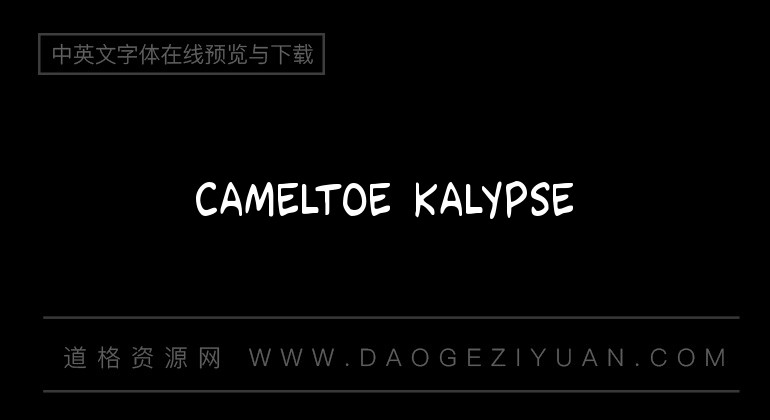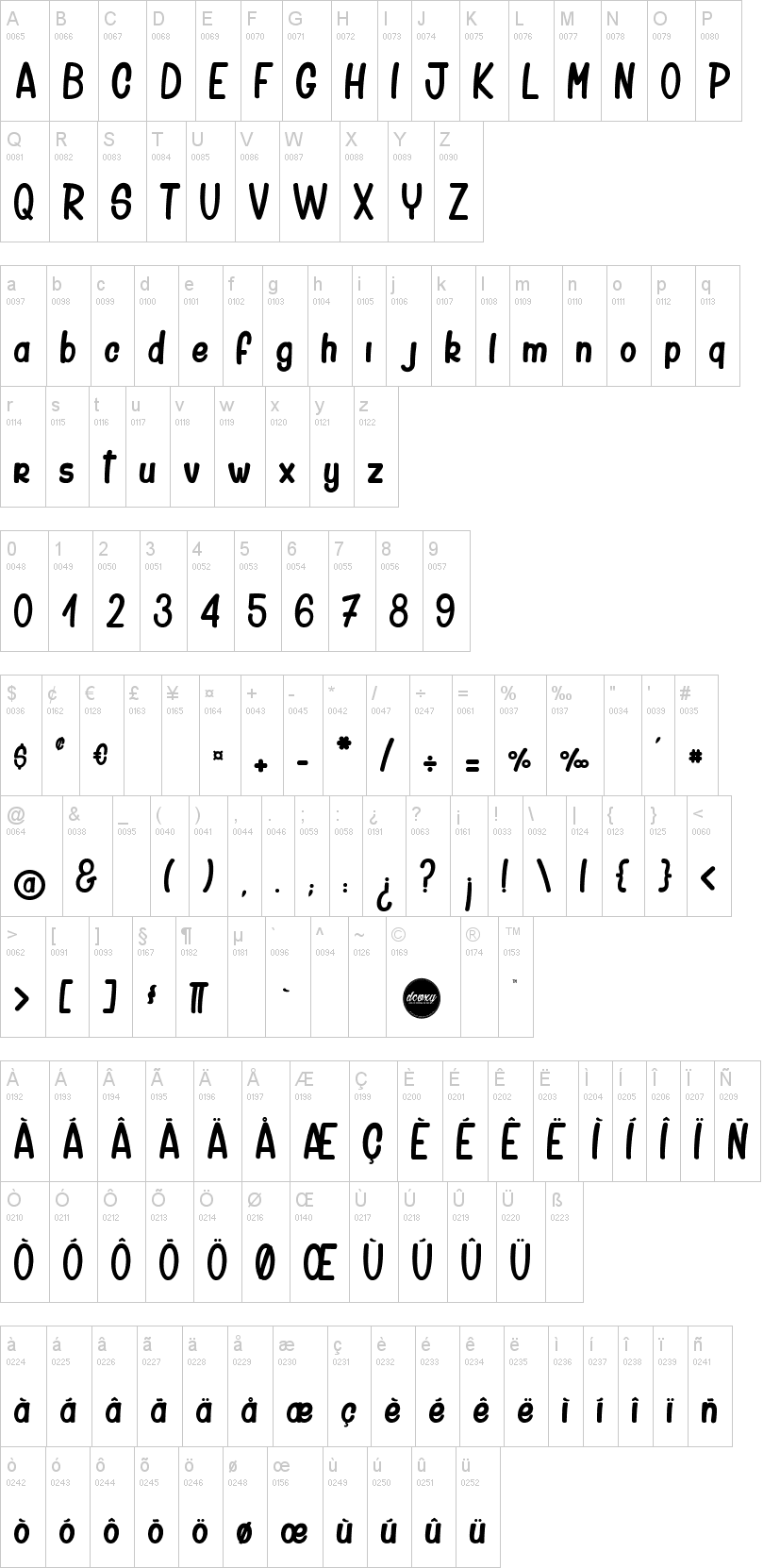
? Cameltoe Kalypse 字体是一款具有独特风格的手写字体,其极具个性的字体设计能够让你的作品更加醒目而具有个性化的特色。它的字体设计结合了一种自然的手写风格,为你的文字添加了更多的活力和深度。它的字体设计具有优秀的可读性,能够让你的文字更加清晰易读。它的字体设计精致而又具有现代感,能够使你的文字更加有趣而又具有时尚感。内容介绍
Cameltoe Kalypse是一款非常不错的手写艺术字体,具有很好的视觉感,适合于文化类的宣传设计、商业类品牌的广告和产品包装设计以及个性化文字排版等较多场景。